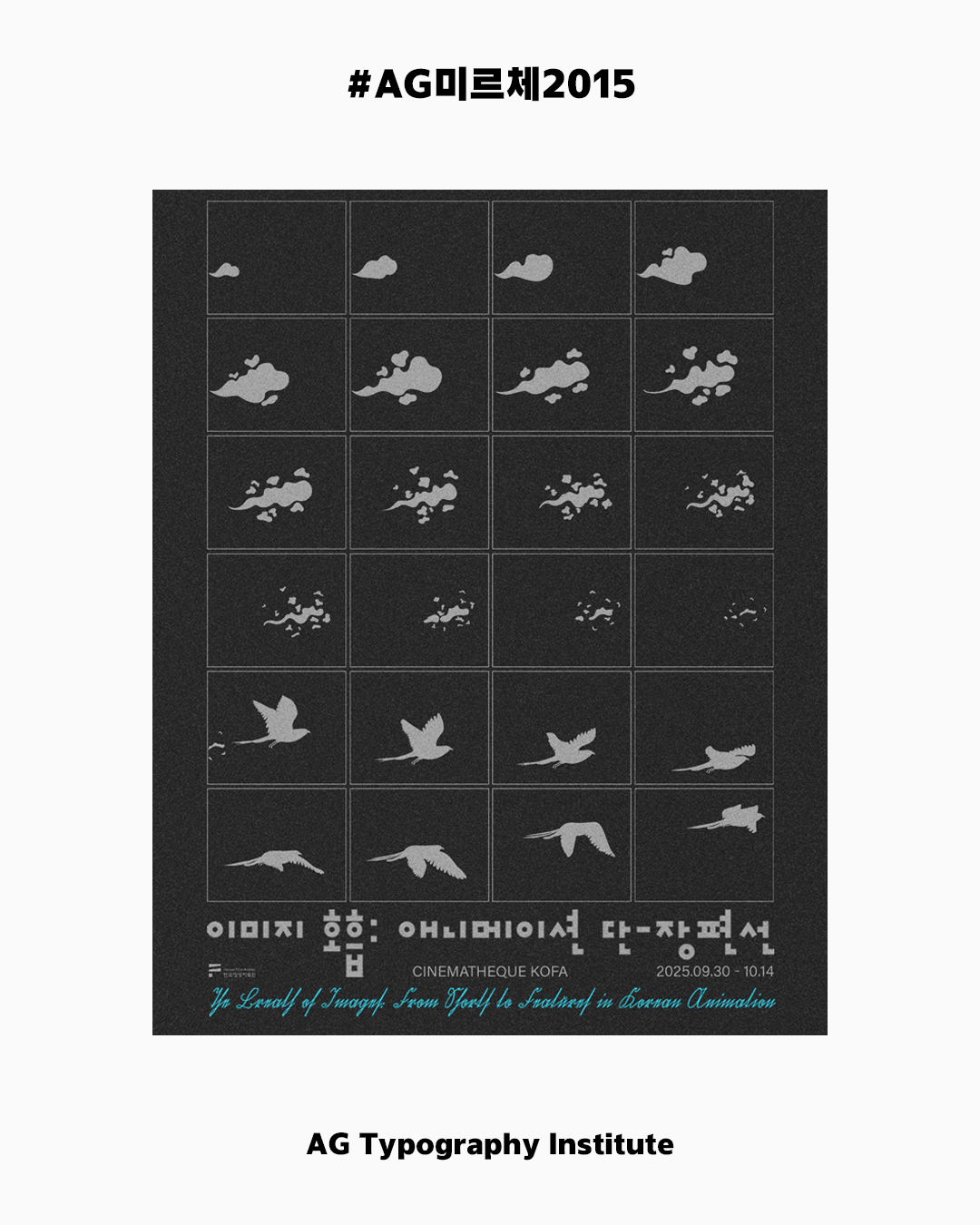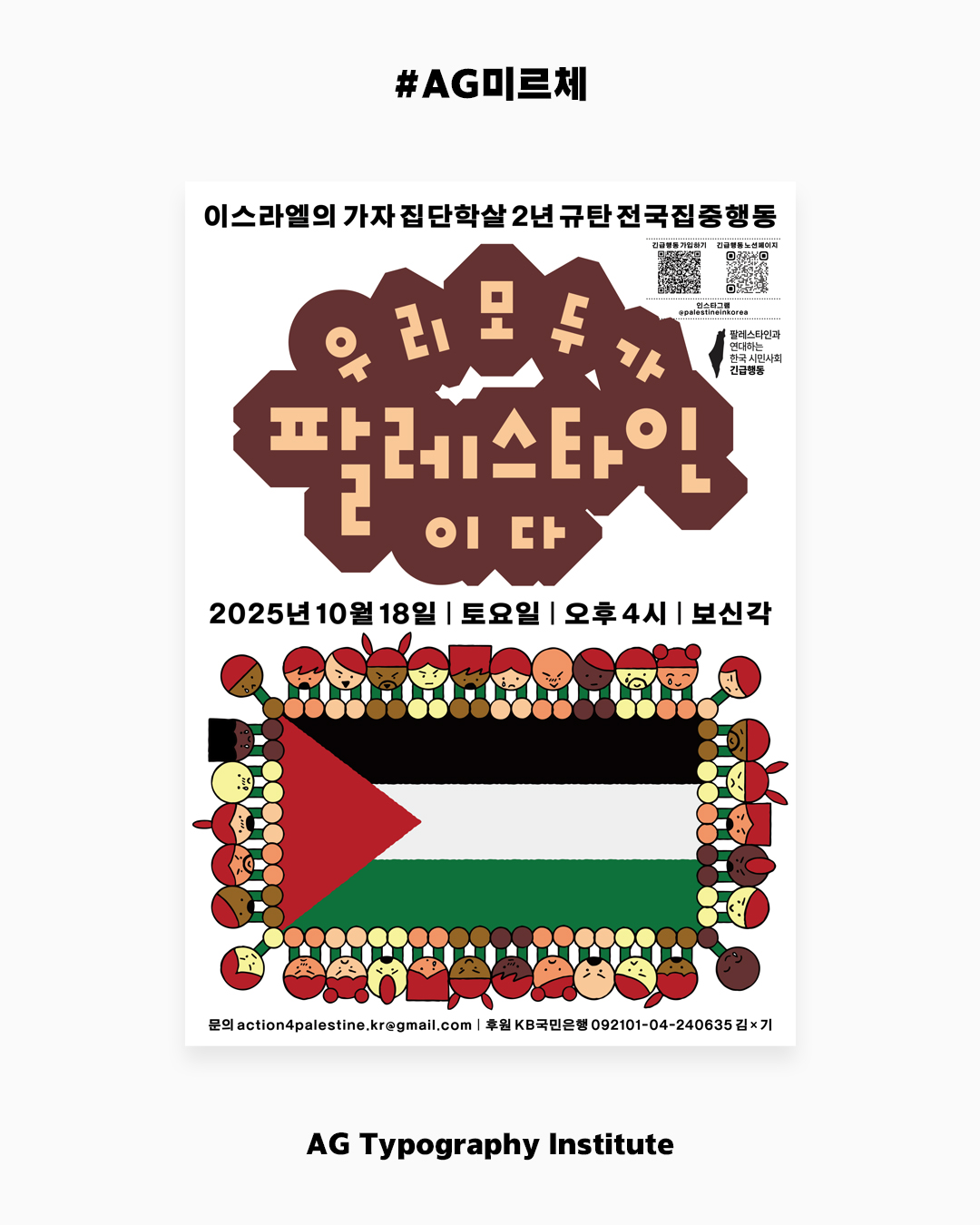
AG 미르체 2015 패밀리
AG Myrrh 2015 Family
〈AG 미르체 2015〉는 1992년 디자이너 안상수가 발표한 탈네모틀 글꼴이다. 〈AG 미르체 2015〉의 한글은 첫닿자 19자, 홀자 21자, 받침 27자를 조합하여 11,172자를 만들었으며, 글자가족을 총 6종으로 판올림 했다.